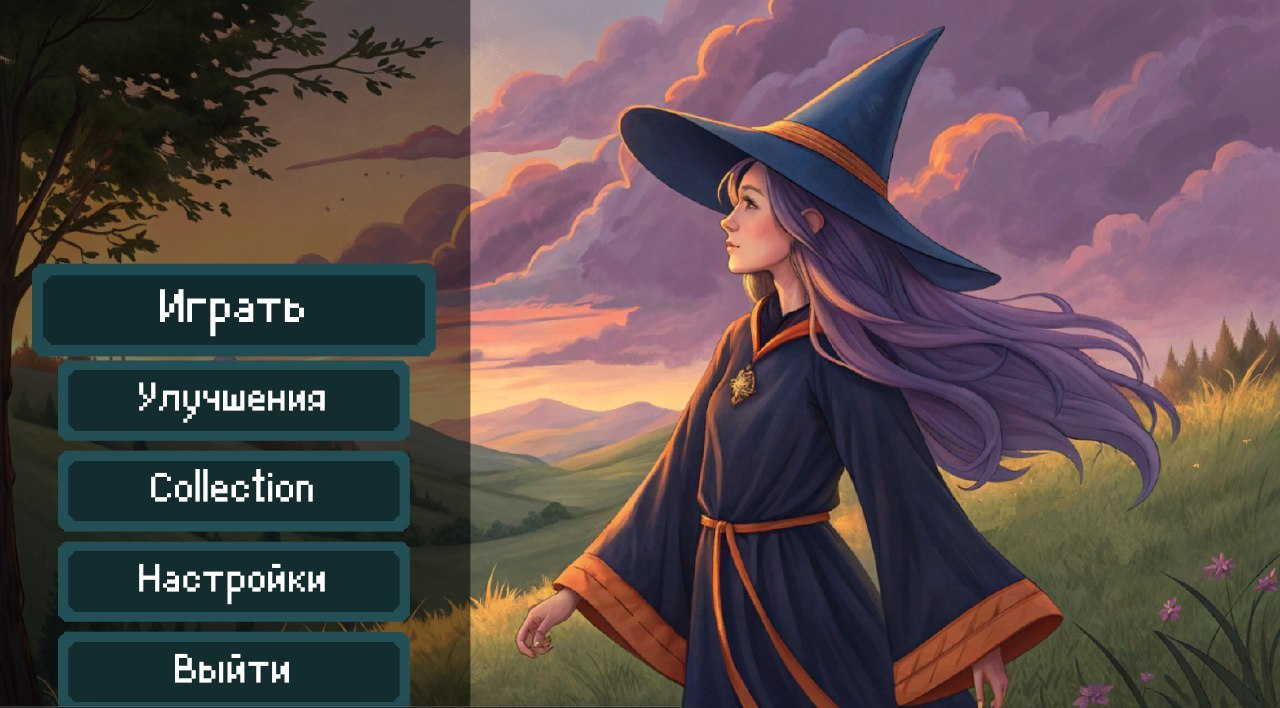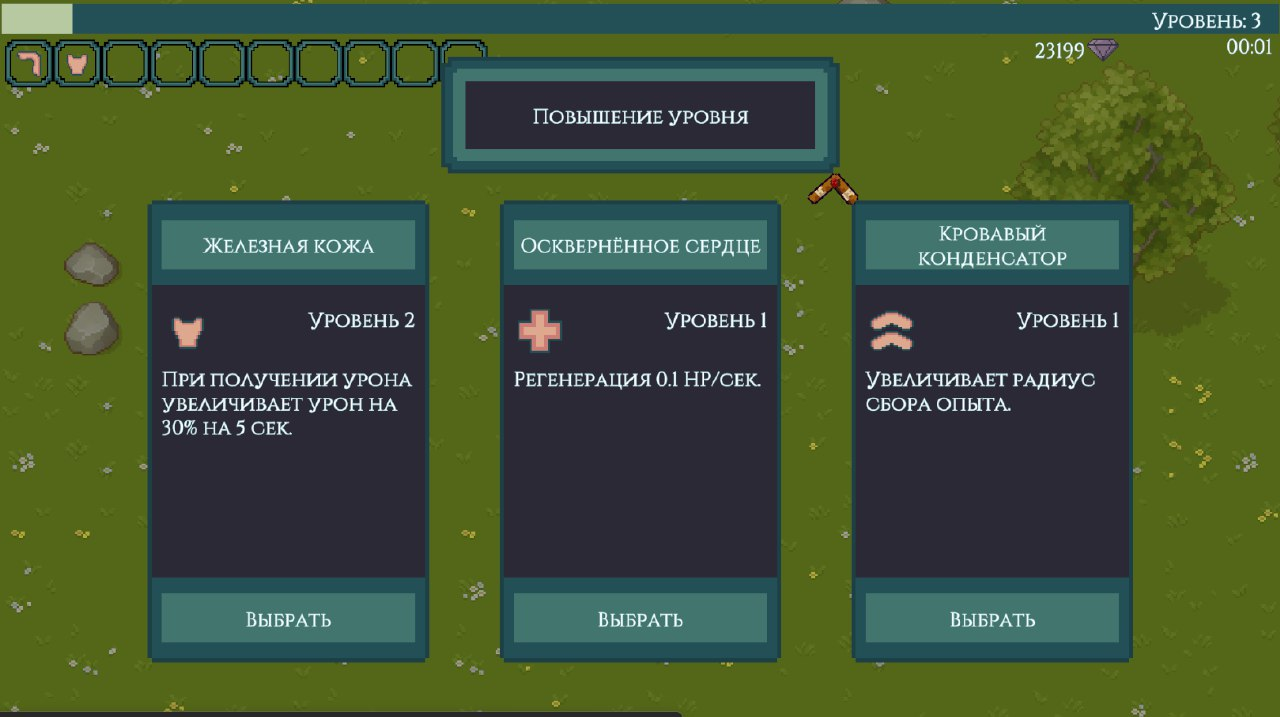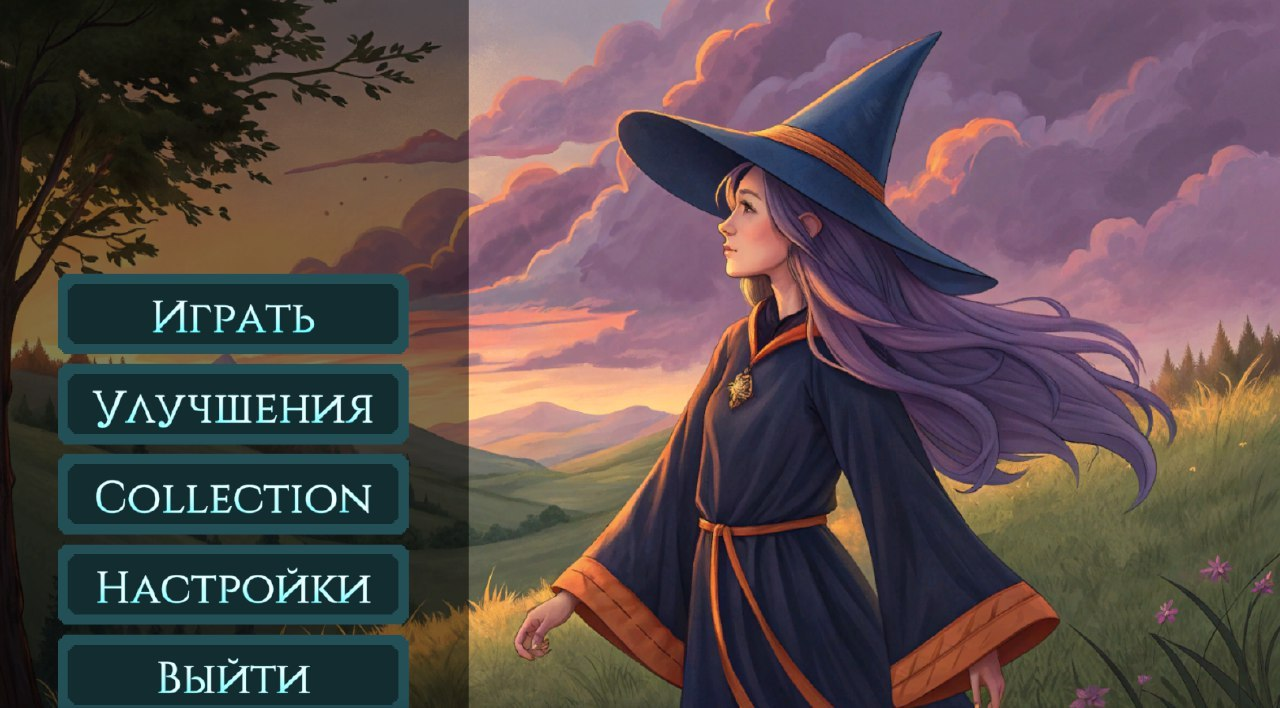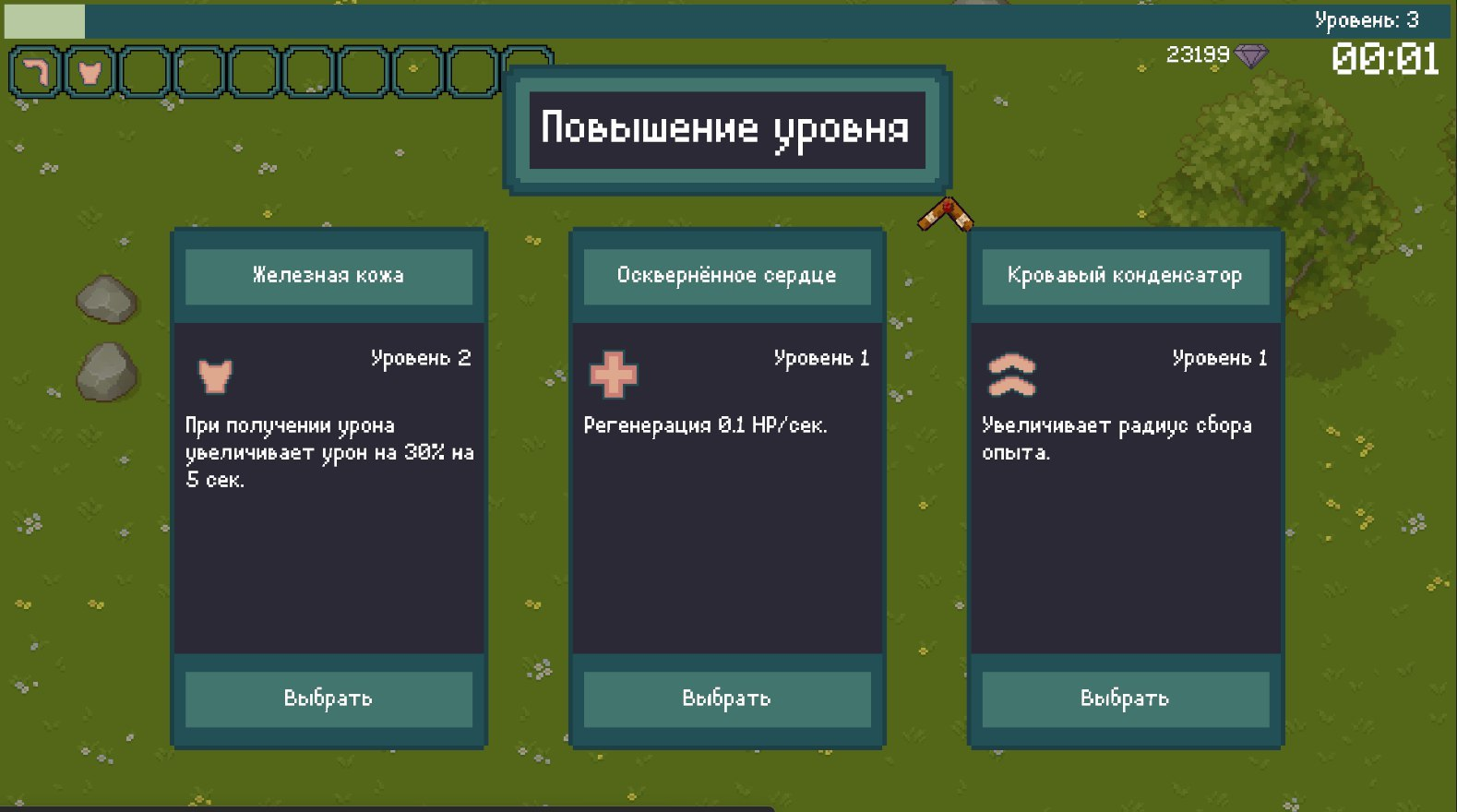
Какой шрифт лучше? Пиксельный или нет
Я делаю свою игру и хочу услышать мнение, какие шрифты вам больше нравятся - пиксельные или нет. Слышал много негатива в сторону пиксельных шрифтов, про плохую читаемость, но у меня с этим проблем нету. Хочу узнать ваше мнение.
P.S для комментов про несочетаемость с артом, я его скорее всего заменю и в целом сама игра в пиксель арте сделана, кроме арта в главном меню.
P.S.S Видимо придется делать выбор шрифта, так как мнения разделились, я в целом изначально так и думал сделать, но не знаю насколько это будет возможно реализовать.